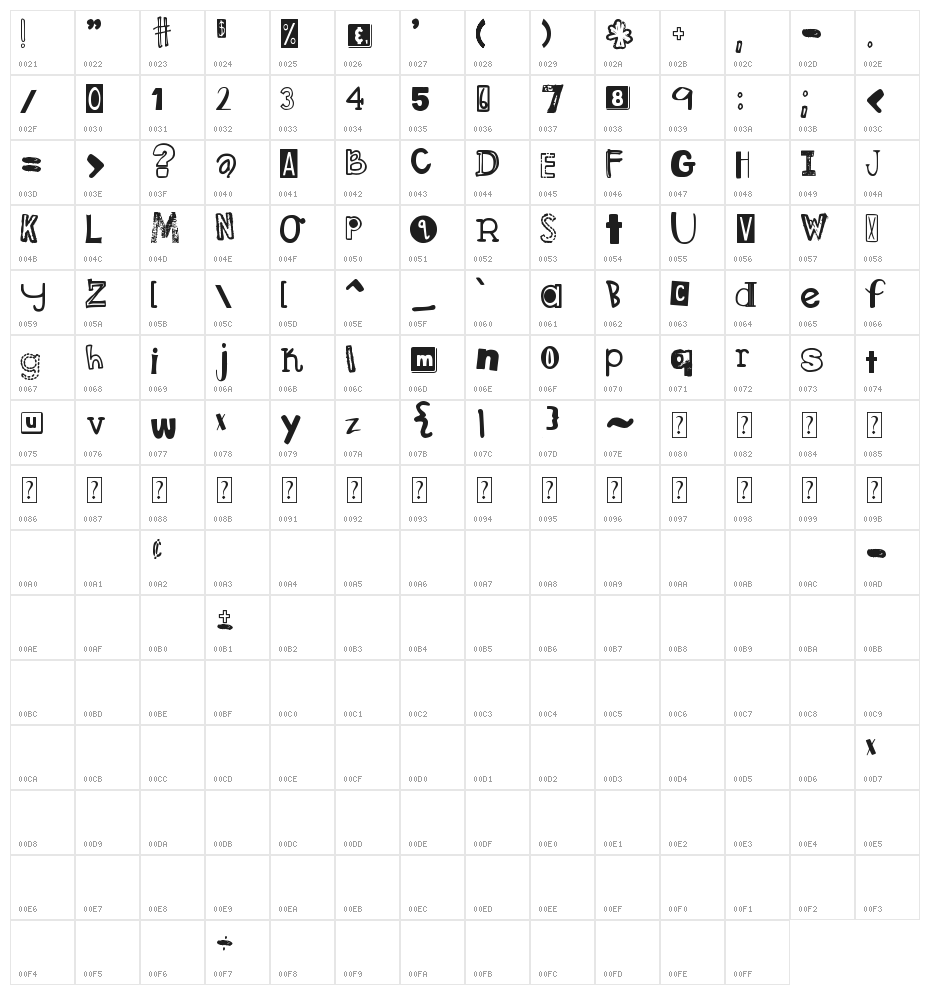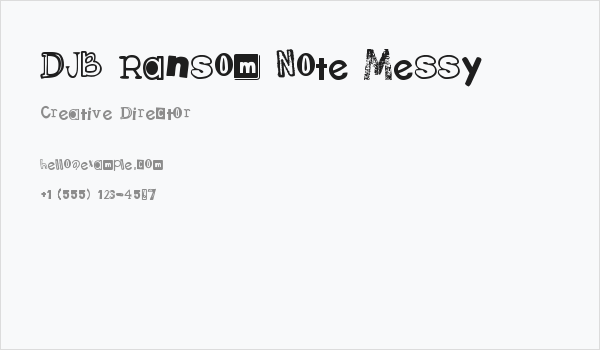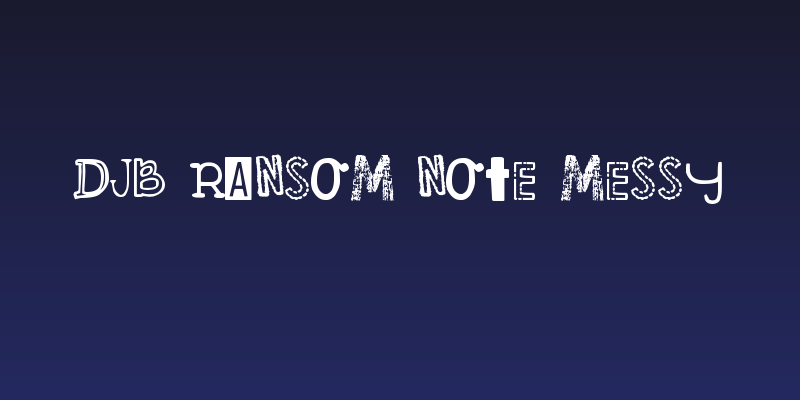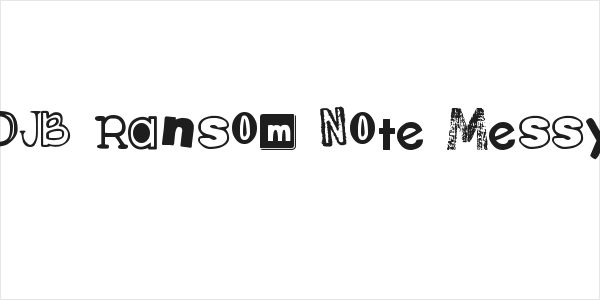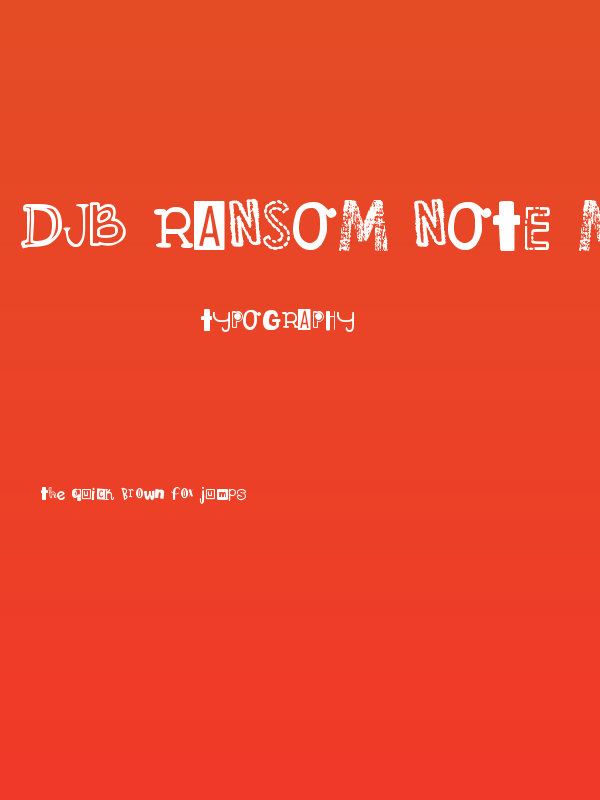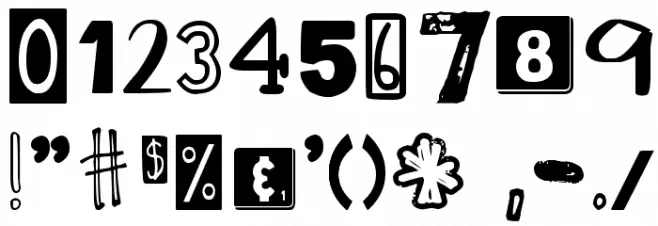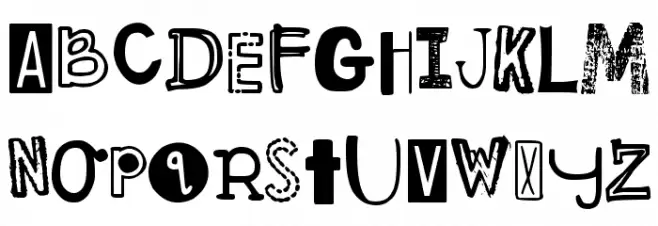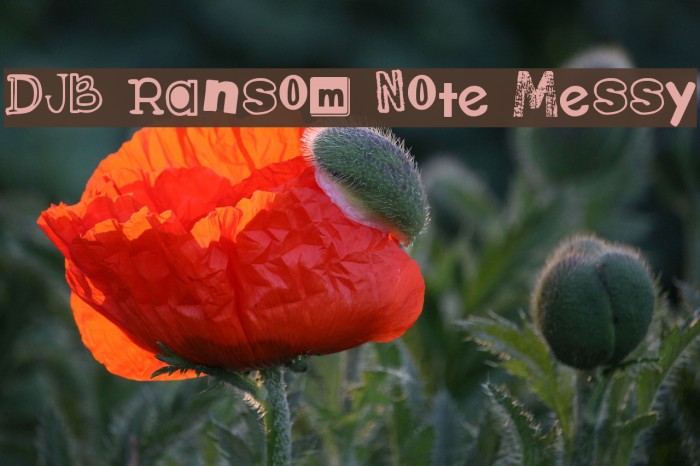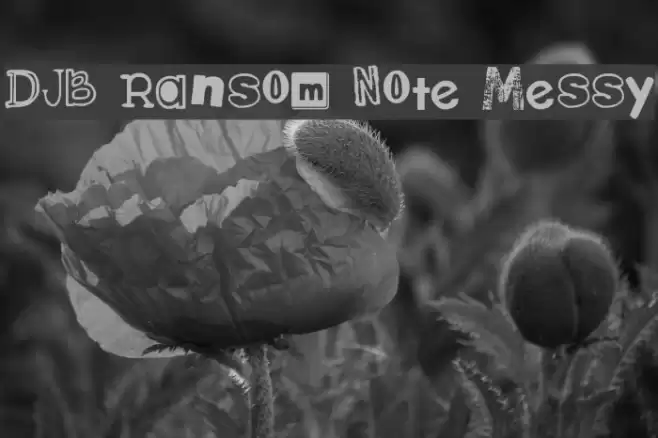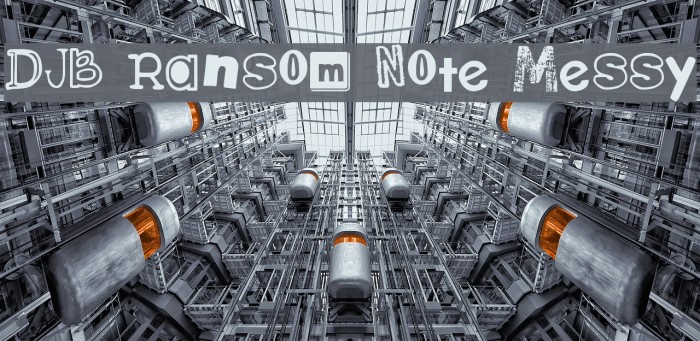
DJB Ransom Note Messy Font
Fonts by Darcy Baldwin {fontography}
| Caso de uso | Headlines, Posters, Creative Designs |
| Proyectos propuestos | Ideal for creative projects like posters, party invitations, scrapbook designs, and any work that benefits from a playful, informal style. |